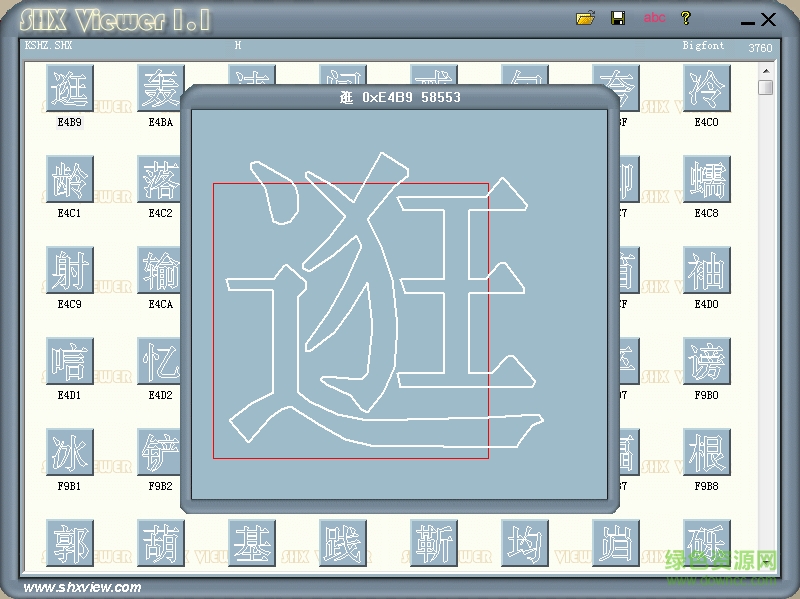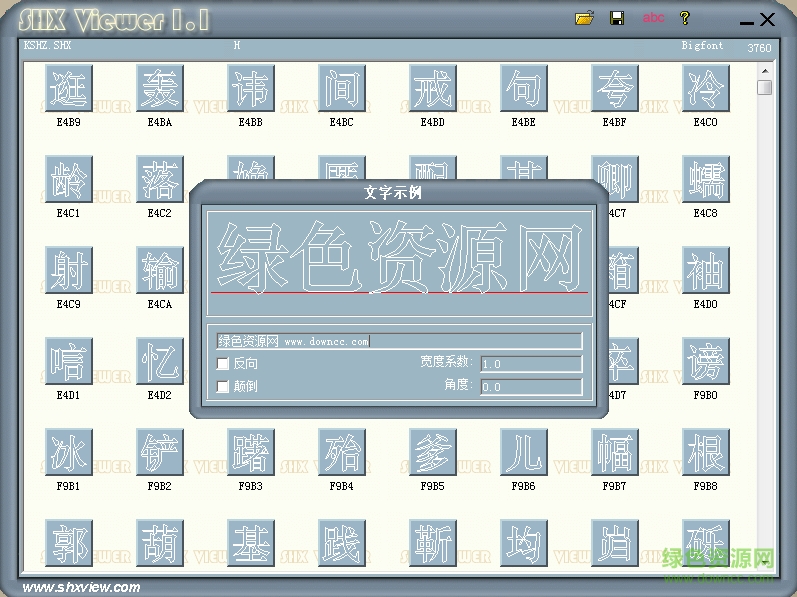
kshz.shx是一款結(jié)合宋體書(shū)法特點(diǎn)的cad字體,粗細(xì)明顯棱角分明,有著宋朝婉約清秀的古風(fēng)韻味,讓你的設(shè)計(jì)更能打動(dòng)人心,綠色資源網(wǎng)歡迎大家免費(fèi)下載!
kshz.shx以宋體為模的空心字體,共由3760個(gè)漢字組成,是autocad中的大字體系列,讓藝術(shù)創(chuàng)作、平面設(shè)計(jì)的文字文字內(nèi)容更加立體生動(dòng)。
宋體字是宋朝發(fā)明的一種漢字印刷字體??蚣芙Y(jié)構(gòu)象黑體,筆劃?rùn)M平豎直,且有粗細(xì)變化:橫細(xì)豎粗,橫劃末端有裝飾三角形,豎劃、撇劃、鉤劃(橫、豎、撇、彎鉤)、利刀等,開(kāi)端也有裝飾三角形。宋體字常見(jiàn)有兩種類型:1豐滿型:帶有較明顯的黑體特征,但不象黑體那樣嚴(yán)肅莊重。方點(diǎn)(出筆尖收筆方)、撇捺、鉤等筆劃比較豐肥,給人以飽滿、厚重之感;2瘦勁型:圓點(diǎn)(象水滴造型)、撇捺、鉤等筆劃比較瘦勁,給人清秀之感。宋體字字型一般為方型,根據(jù)內(nèi)容和版面需要可以適當(dāng)壓扁和拉長(zhǎng),以求活潑輕快之感。筆劃的粗細(xì)也可以做適當(dāng)調(diào)整。